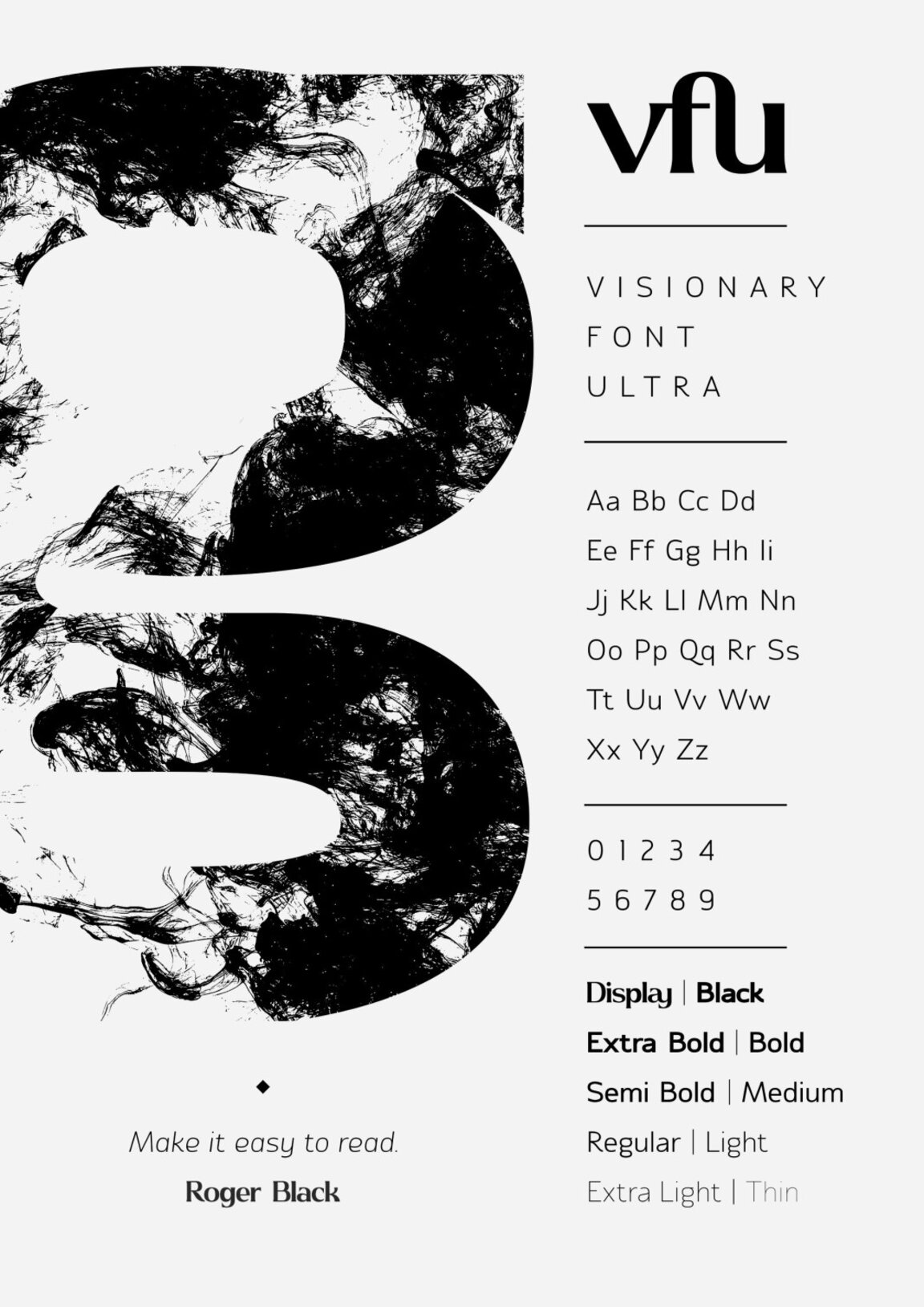
Студентски шрифт от Варненския свободен университет с международен успех
Шрифтът "VFU" (Visionary Font Ultra), създаден от Володимир Федотов, студент в трети курс на специалност "Графичен дизайн" във Варненския свободен университет (ВСУ) "Черноризец Храбър", получи признание на международно ниво. Той е един от тримата представители на България, селектирани за участие в изложбата на престижното Международно триенале на типографията "Проф. Юзеф Мрошчак", което ще се проведе в Полша.
Изложбата ще бъде открита на 21 март 2025 г. в Музея на печата в град Нови Тарг. Тя ще включва 50 от най-добрите проекти в конкурсната програма, представящи млади творци от Полша, Дания, Германия, Великобритания, Франция, Нидерландия, САЩ, Аржентина, Япония и Китай. Сред тях ще бъде и работата на Володимир Федотов – оригинален авторски шрифт, в който е вплетена и международната абревиатура на Варненския свободен университет – vfu.bg.
Процесът на създаване на "VFU"
Шрифтът "VFU" е разработен в рамките на дисциплината "Шрифт" под ръководството на Ани Димитрова – един от водещите български шрифтови дизайнери. Проектът включва 19 разновидности, разпределени в 9 дебелини, италик версия и дисплейна версия, като поддържа писане на 95 езика, включително и кирилица.
В интервю за "Нашият ден" Володимир Федотов сподели за предизвикателствата при създаването на шрифтове: "Процесът е сложен – от начертаването на буквите, до тяхното позициониране в самия шрифт, после презентацията и представянето пред обществото. Това изисква много търпение, но най-трудната част е визуализацията – как да се представят качествата на шрифта и как да се използва ефективно."
От учебен проект до международна изложба
Интересът на Володимир Федотов към типографията се заражда от неговата работа като графичен дизайнер. "Започнах да правя няколко шрифта, които бяха добре приети от обществото, и така се насочих в тази посока", споделя той.
Шрифтът "VFU" първоначално е създаден като част от учебен проект, в който студентите трябвало да разработят само отделни букви. Володимир обаче решил да създаде цялостен шрифт. Именно този проект е забелязан и избран за участие в престижното Международно триенале на типографията в Полша.
Значението на участието в триеналето
Международното триенале на типографията в Нови Тарг е сред най-престижните форуми за типографско изкуство, събиращ студенти, млади художници и утвърдени графични дизайнери от цял свят. Полската школа по плакат и типография е известна със своите традиции и иновации, а участието в този конкурс е сериозно признание за всеки творец.